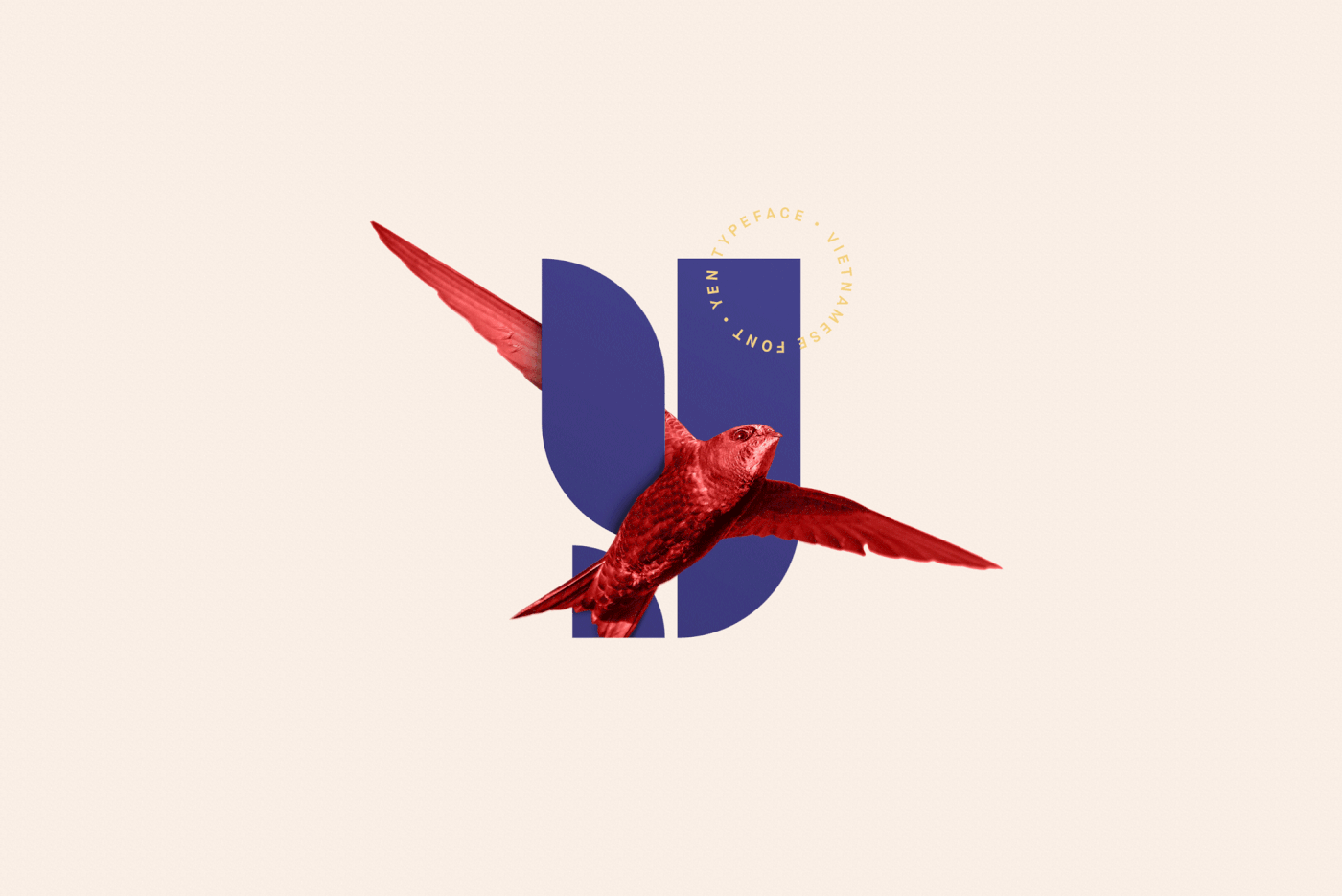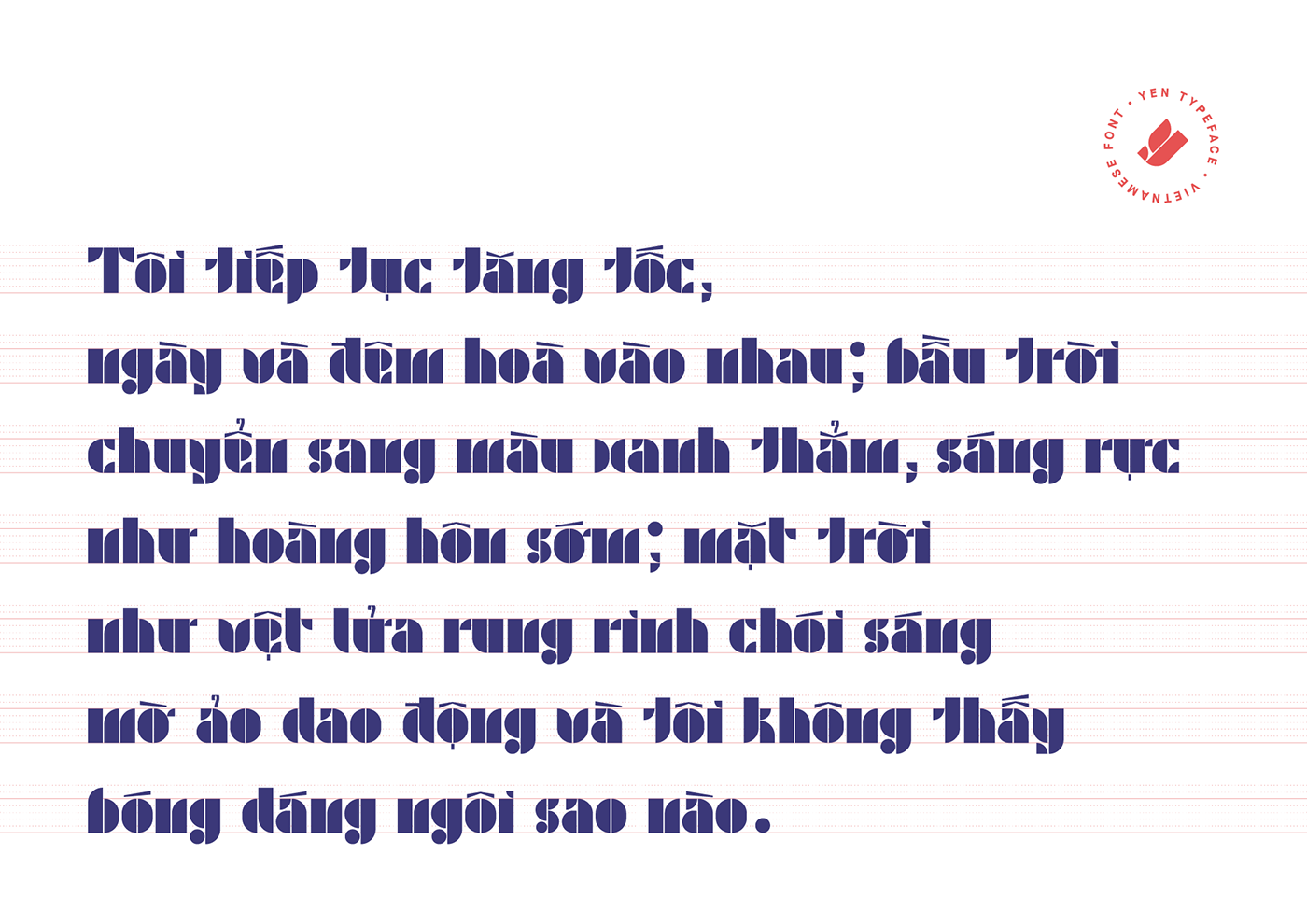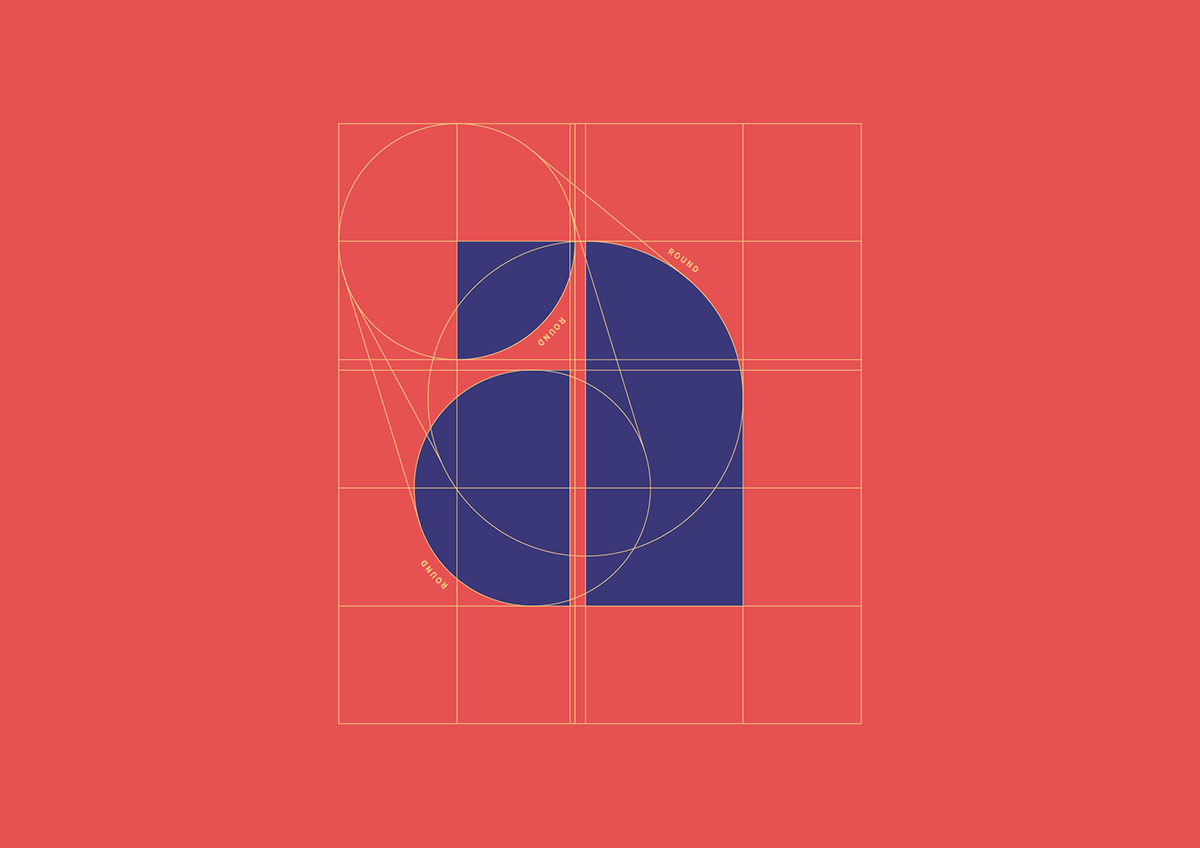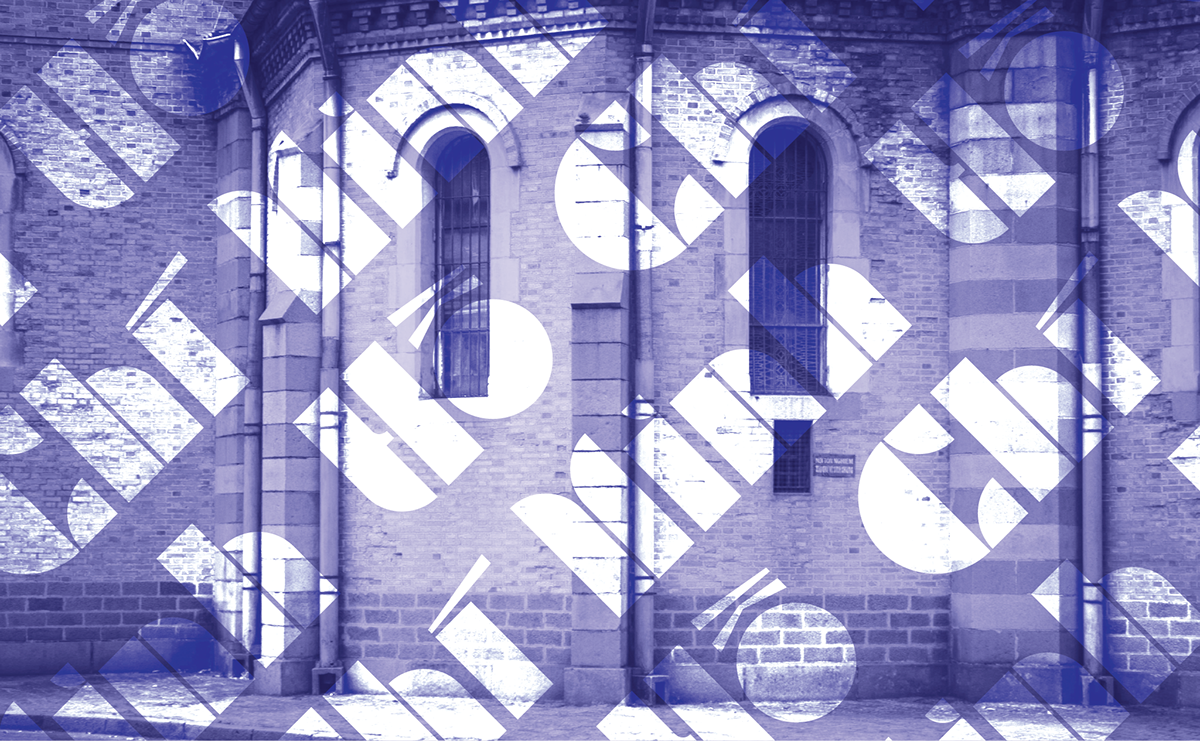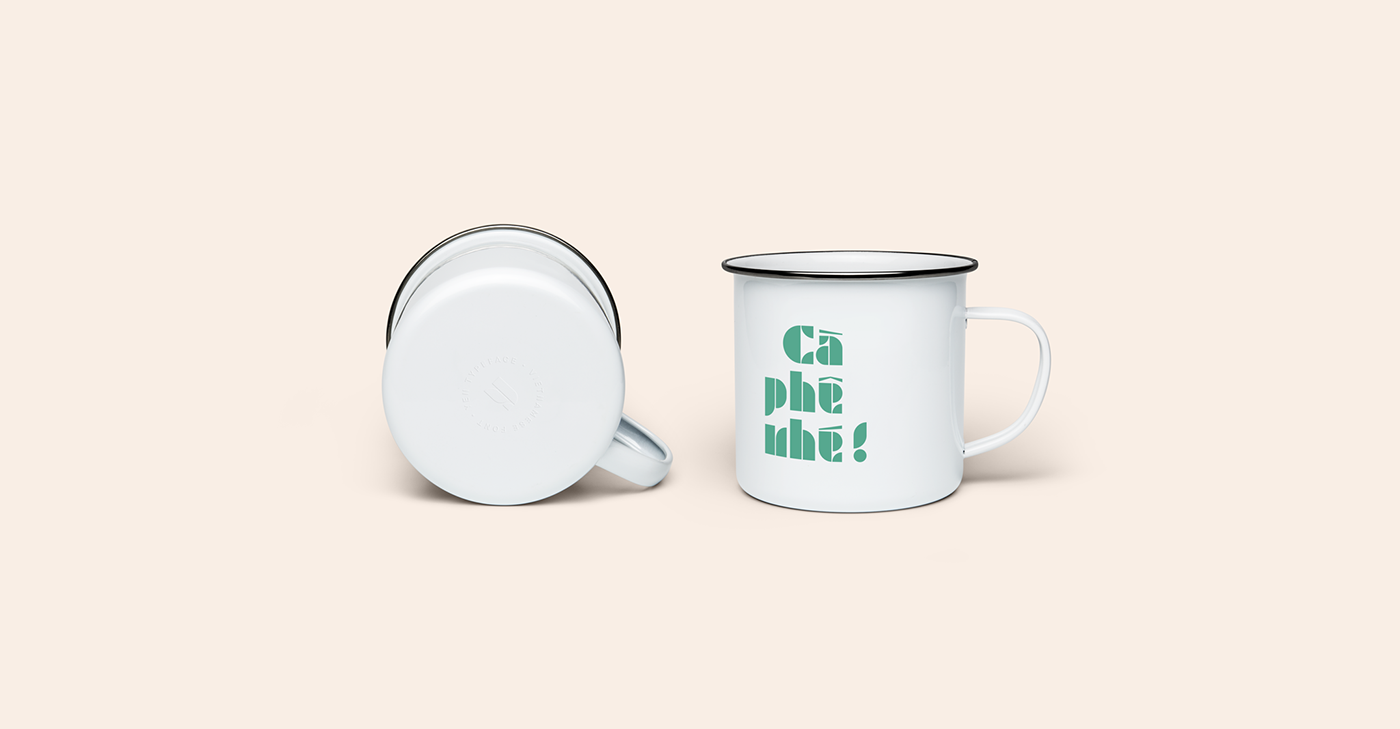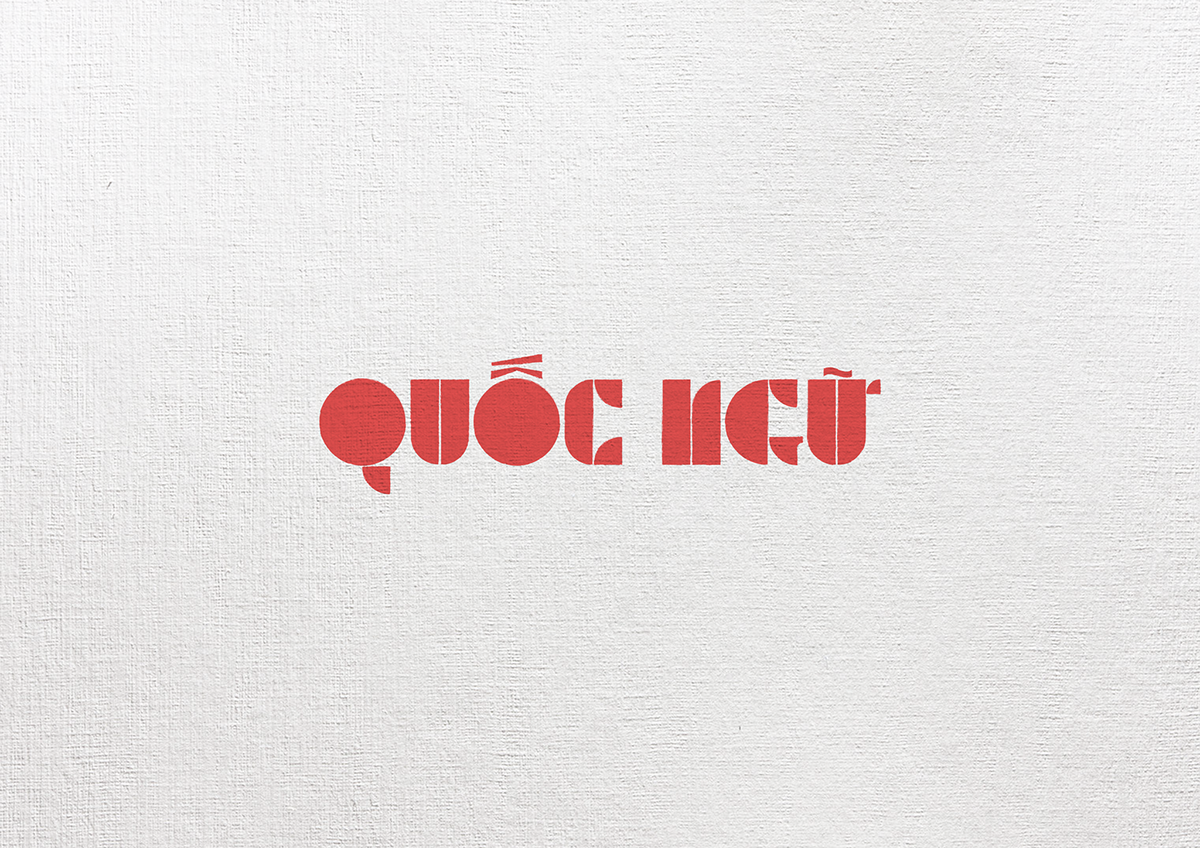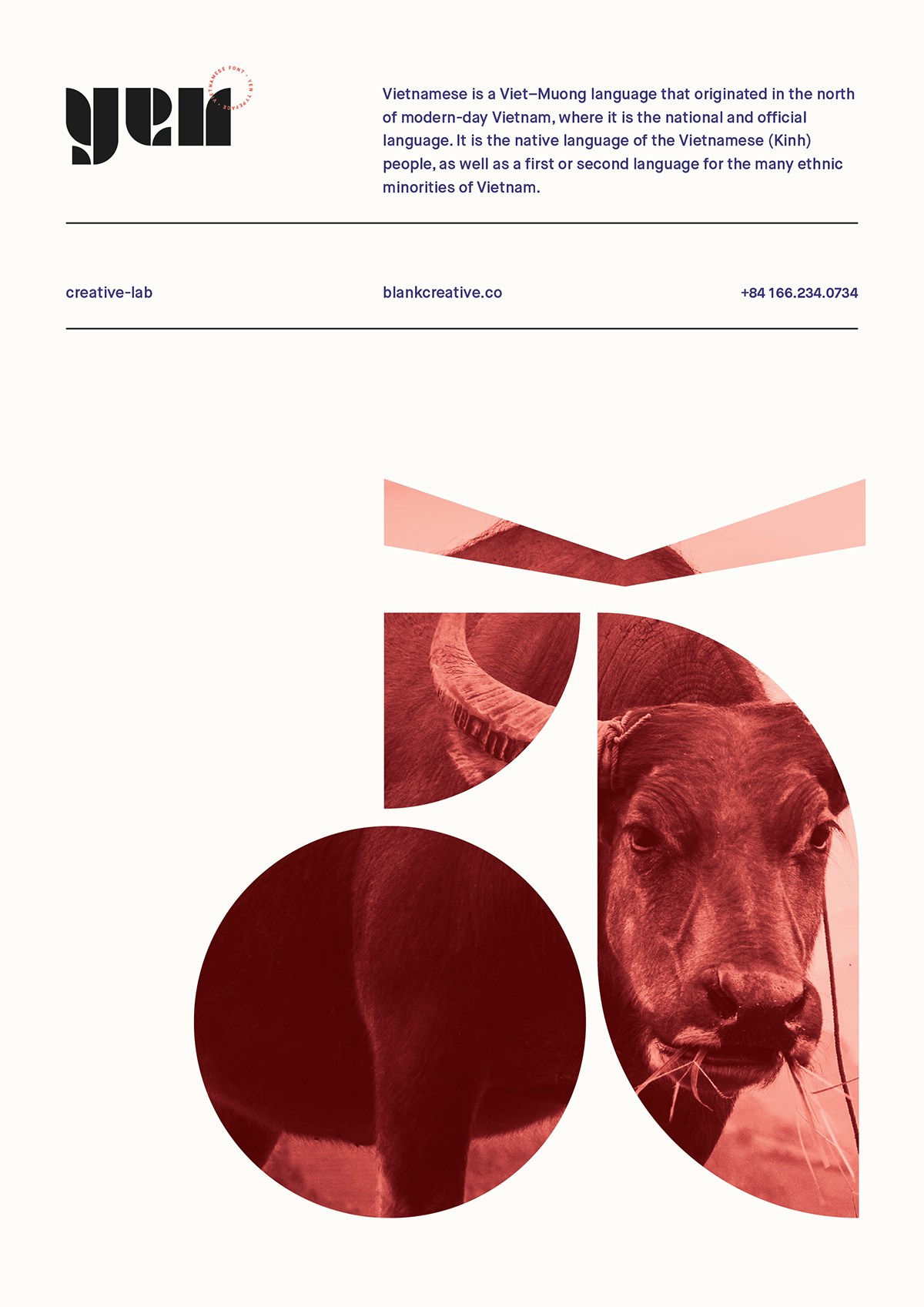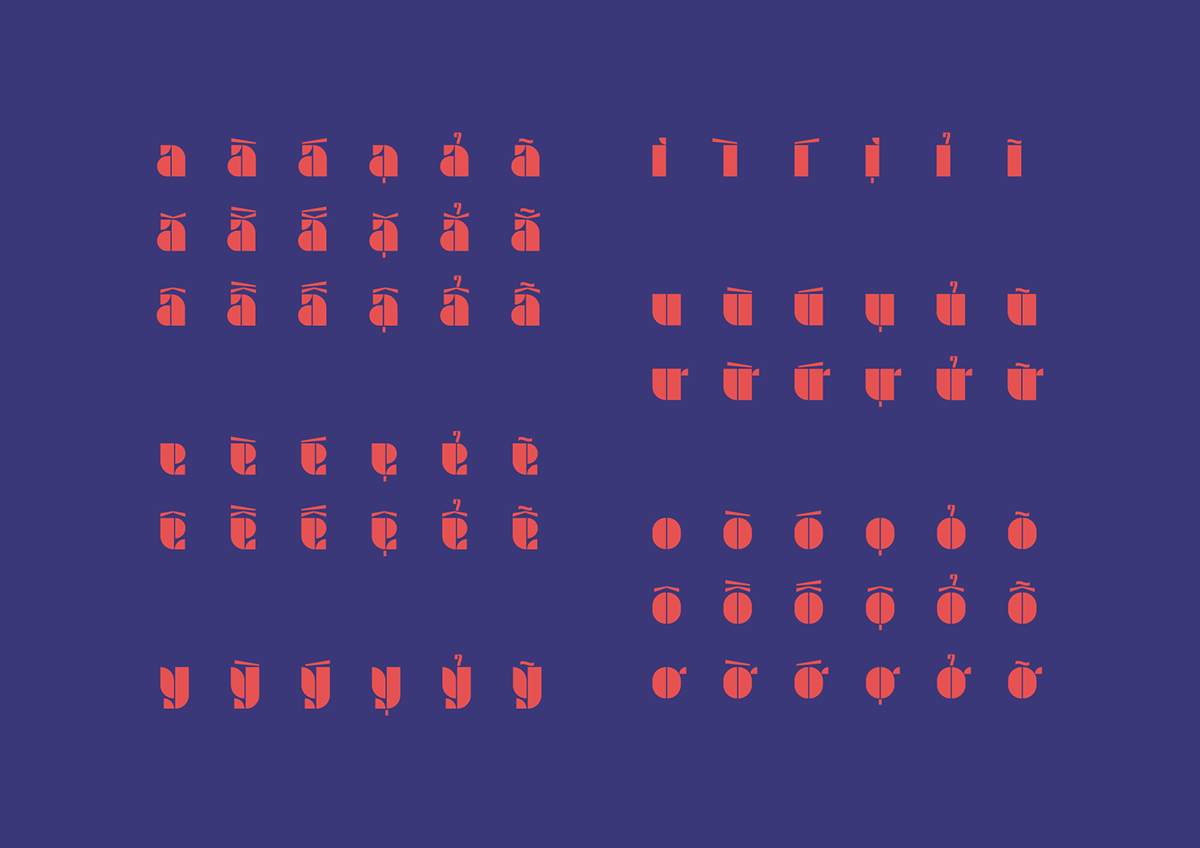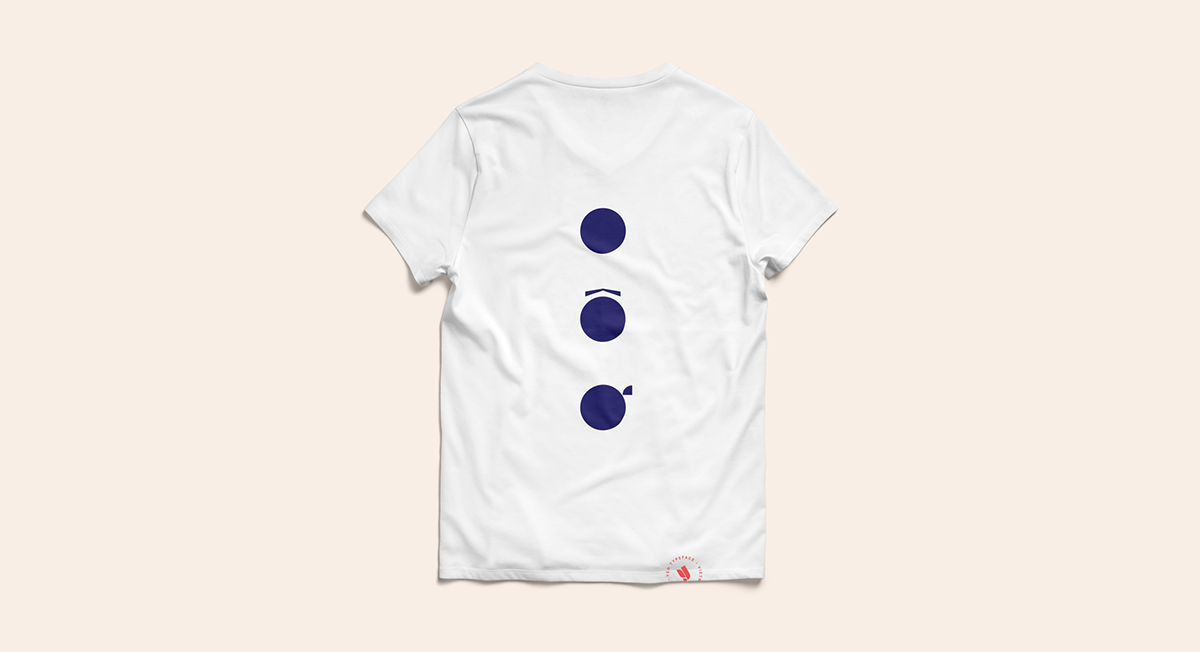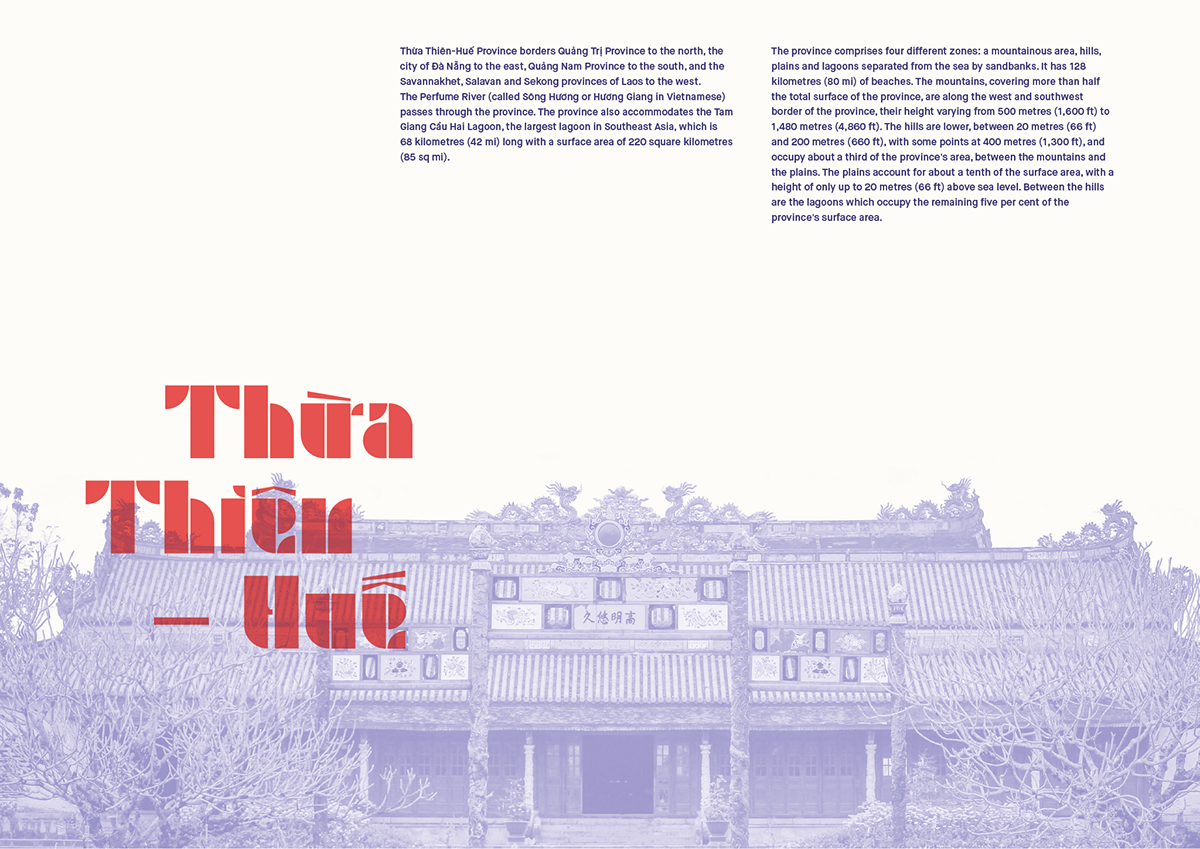
Nhà thiết kế Đỗ Trọng Đạt (đến từ Blank Studio) giới thiệu bộ YEN typeface đậm hồn quốc ngữ lấy cảm hứng từ quan niệm của người Việt Nam về vòng tròn, được coi là bầu trời và hình vuông như mặt đất, cùng những đặc trưng châu Á.
Bộ YEN typeface:
Tiếng Việt đã được phát triển và biến đổi trong suốt thời kỳ lịch sử Việt Nam. Ngày nay, ngôn ngữ tiếng Việt đã được hoàn thiện và sử dụng trên cả nước chữ S, còn được gọi là “Quốc Ngữ” (Ngôn ngữ Quốc gia). “Quốc Ngữ” sử dụng các ký tự Latinh gồm: Sắc (giai điệu tăng dần), Huyền thoại, Hỏi (Gia tăng giai điệu), Ngã (giai điệu cao), Nặng (chấm âm), Ngang (giọng điệu phẳng).
Bằng cách tạo ra cái nhìn mới và đặc biệt cho các đặc trưng Việt Nam, Blank đã có ý tưởng kết hợp các chữ tượng hình châu Á với các ký tự Latinh nhưng không mất nguồn gốc. Lấy cảm hứng từ quan niệm của người Việt Nam về vòng tròn, được coi là bầu trời và hình vuông như mặt đất, kiểu chữ YEN ở đây được tạo ra. Kiểu chữ YEN là phông chữ hiển thị giới hạn về ngôn ngữ mà chỉ áp dụng đối với tiếng Việt mà không có các chữ cái J, Z, W, F.